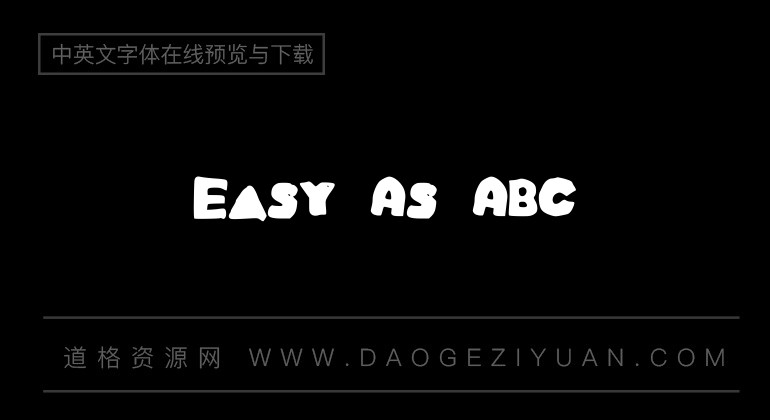
Easy As ABC 字体是一款拥有朋克风格的英文字体,由比利时设计师Dries Wiewauters设计,它采用丰富的细节和技术,使字体看起来更加有趣,更加现代化,更有辨识度。它可以用于文字排版,也可以用于标志和海报设计,是一款极具创意的字体。内容介绍
Easy As ABC是一款非常不错的手写艺术字体,具有很好的视觉感,适合于文化类的宣传设计、商业类品牌的广告和产品包装设计以及个性化文字排版等较多场景。